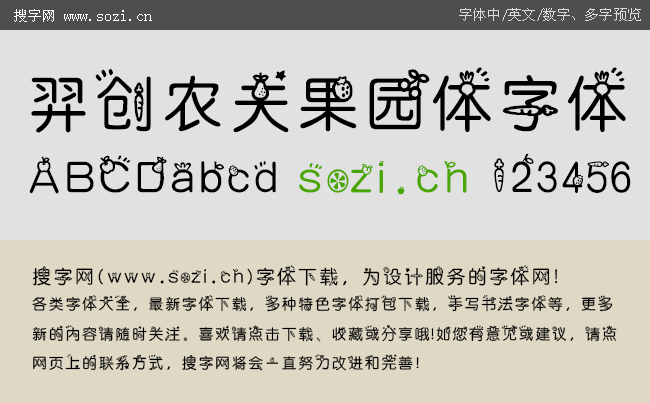
羿創(chuàng)農(nóng)夫果園體字體
搜字網(wǎng)給大家提供一款羿創(chuàng)農(nóng)夫果園體字體手機(jī)中文字體下載。這款手機(jī)字體是以圓體字體為原形,筆畫間嵌入了可愛的卡通水果圖案。在具備圓體清晰風(fēng)格的同時(shí),卡通味也特別濃,是一款非常可愛的卡通字體,特別適合喜歡手機(jī)字體個(gè)性一些的朋友在手機(jī)上安裝使用。